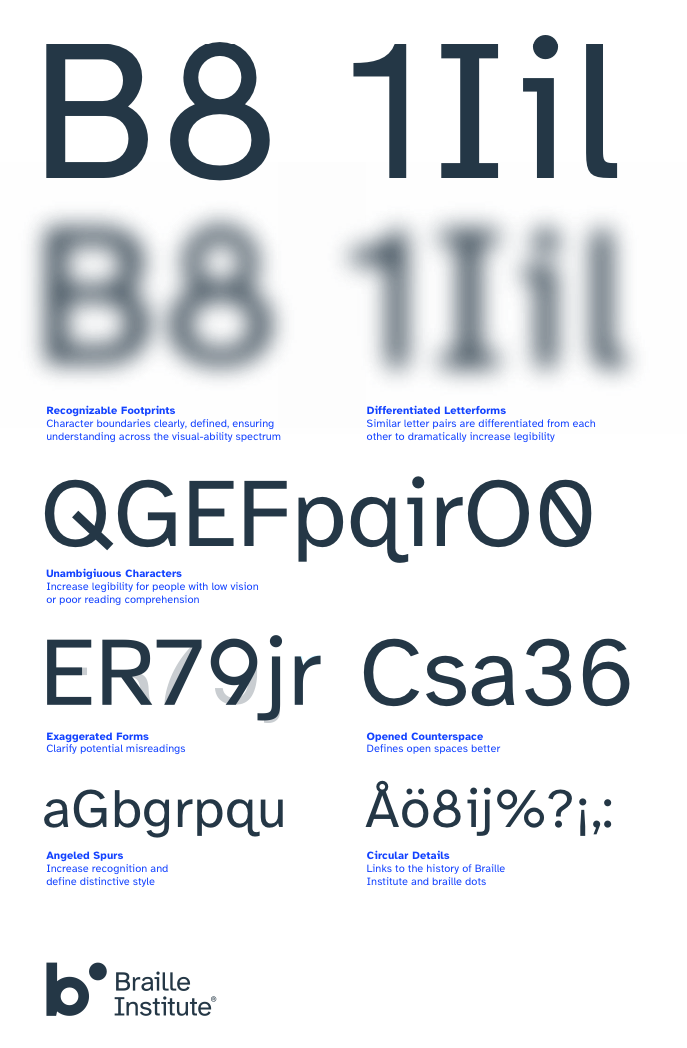
Atkinson-Hyperlegible: neue Schrift des (US) Braille-Instituts
entwickelt mit dem ziel, möglichst leicht lesbar zu sein. also besonders sehbehinderten menschen das lesen zu erleichtern. der weg dorthin war – wie bei vielen zeitgemäßen schriften – die betonung der unterschiede verschiedener glyphen. über die ästhetik kann man streiten, im großen und ganzen ist aber (finde ich) eine halbwegs »normale« grotesk. was mich allerdings davon abhalten wird, die 4 kostenlosen fonts für gewöhnliche kunden-projekte einzusetzen, ist das gemeine »q«. das schwänzchen mag zwar (besonders legasthenikern) die unterscheidung zum »p« erleichtern, für otto normal-auftraggeber wird das ein no go sein.
Das Schwänzchen am q ist im nordamerikanischen Sprachraum durch deren "Fibelschriften" eingeführt ... siehst du auch z. B. hier:
no go
Ja, zumindest eine abgeschwächtere, nicht ganz so spezielle Alternative wäre toll. Allerdings stößt es mir im Texteinsatz überraschenderweise weniger auf, als ich es so solitär betrachtet erwartet hätte.
Nachtrag: Ich finde es bemerkenswert, dass anders als üblich hier das komplexe a genutzt wird.